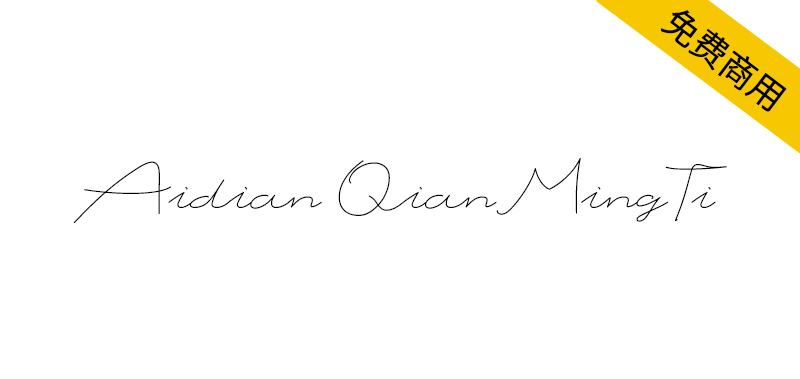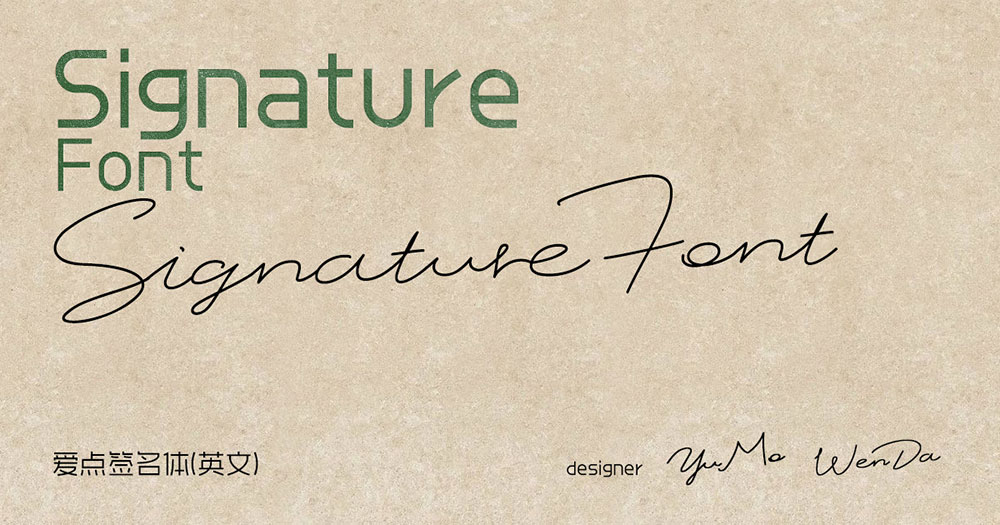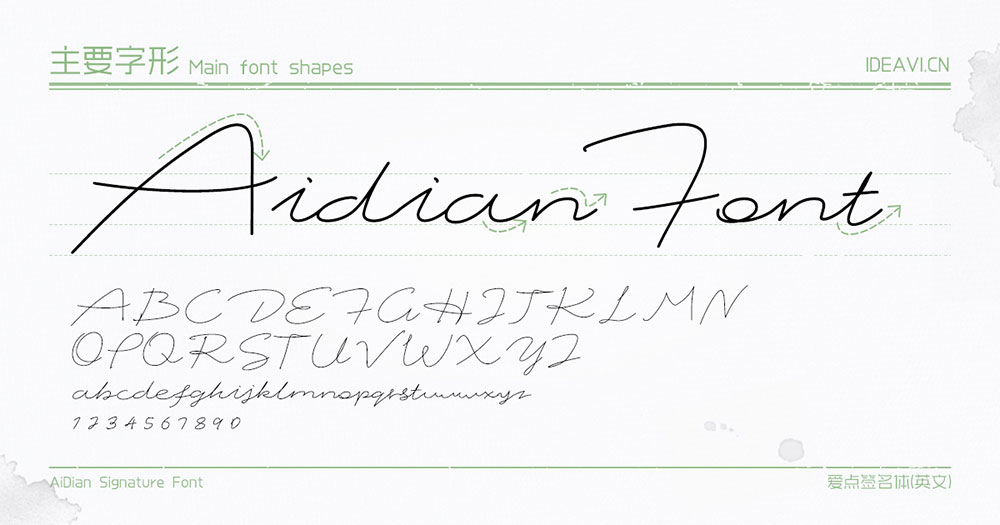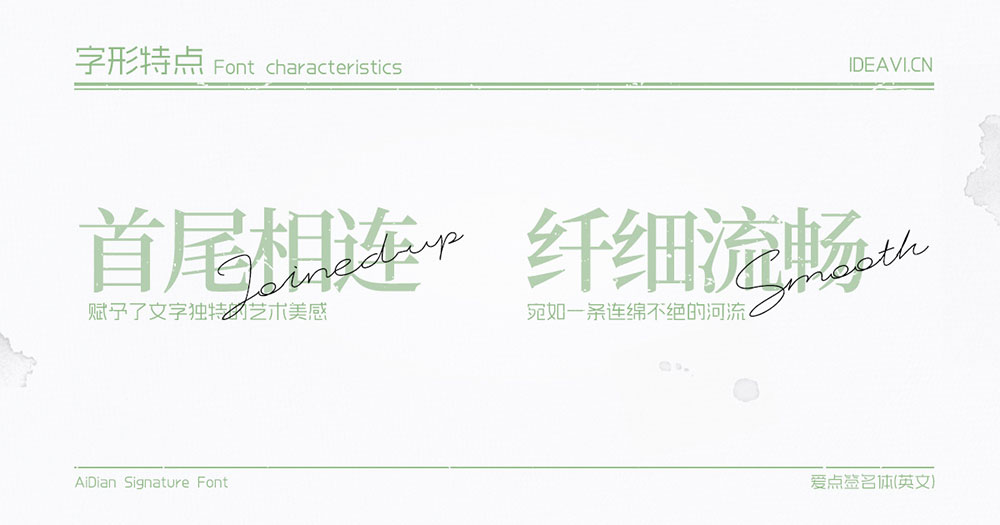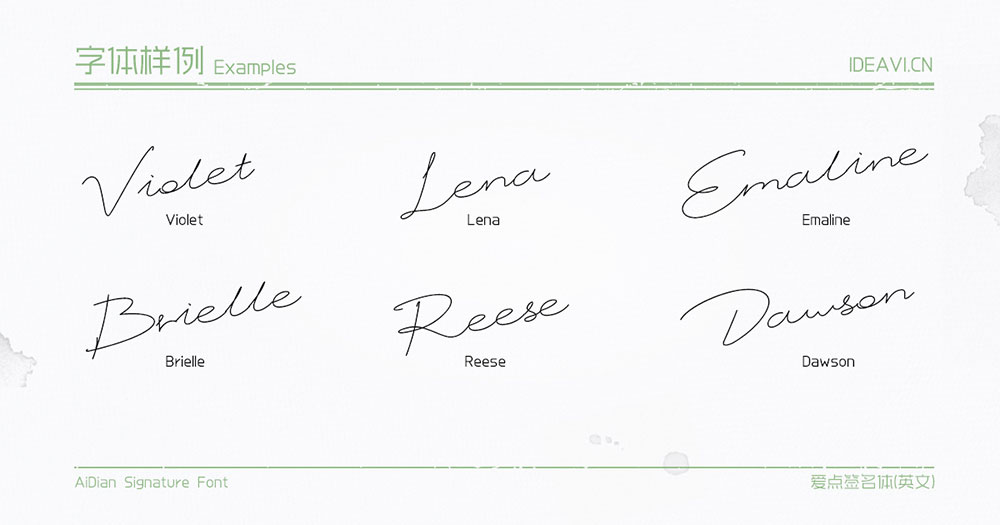
【爱点签名体】首尾相连、纤细流畅的英文签名手写字体
告别字体授权焦虑!这款“爱点签名体”或许就是你一直在寻找的宝藏。它首尾相连,线条纤细流畅,极具艺术美感,专为英文签名设计。最关键的是,个人与企业均可永久免费商用!立即解锁这款签名神器,让你的广告、自媒体和设计作品脱颖而出。
【爱点签名体】首尾相连、纤细流畅的英文签名手写字体
该字体首尾相连的设计赋予了文字独特的艺术美感,字形纤细流畅宛如一条连绵不绝的河流,非常适合用于英文签名使用。